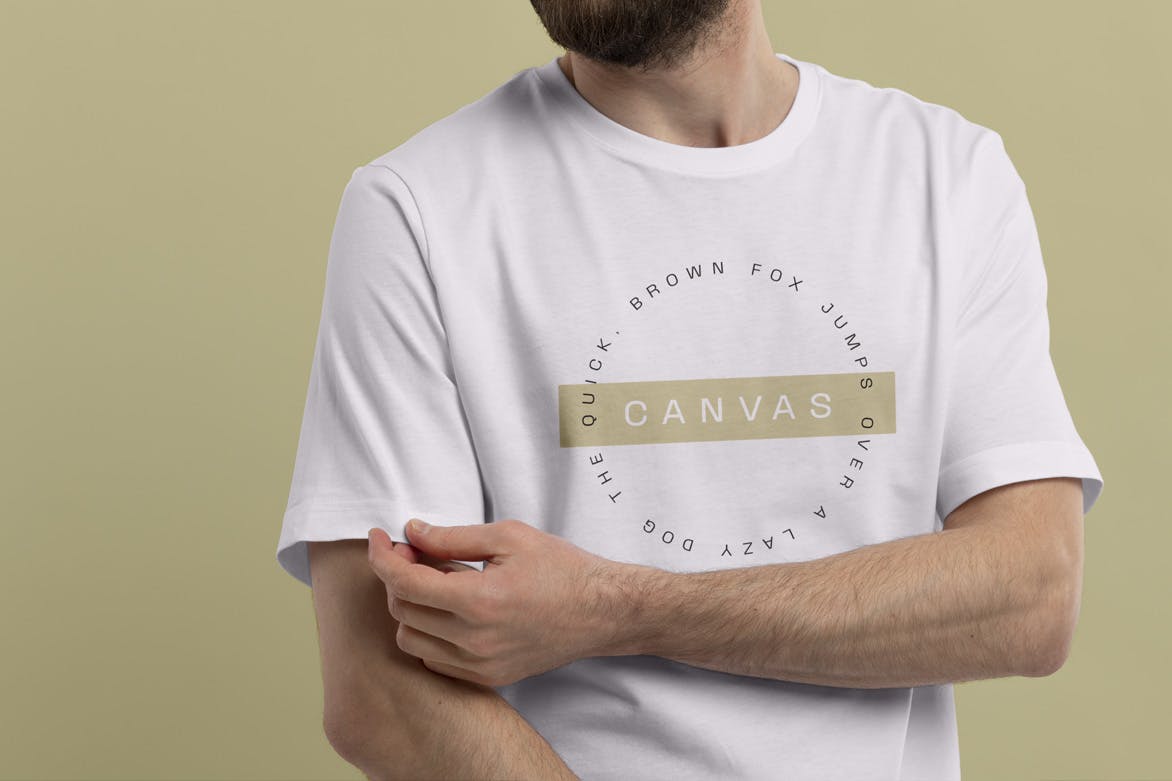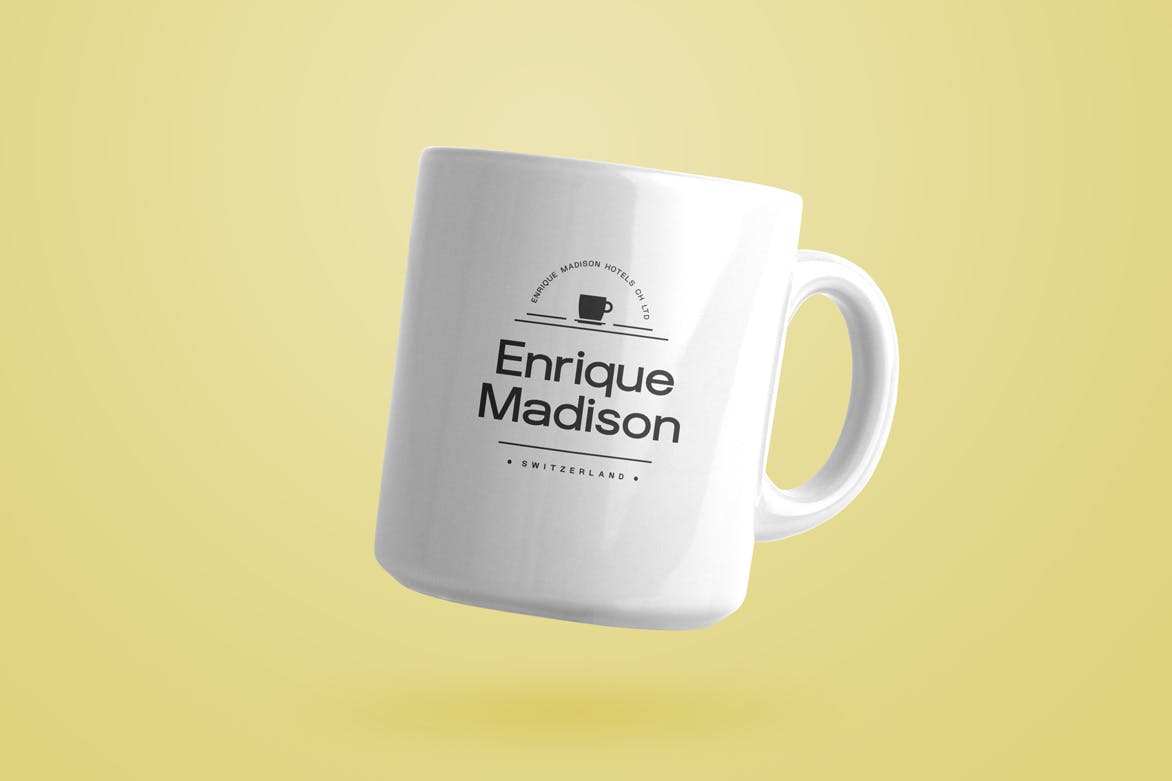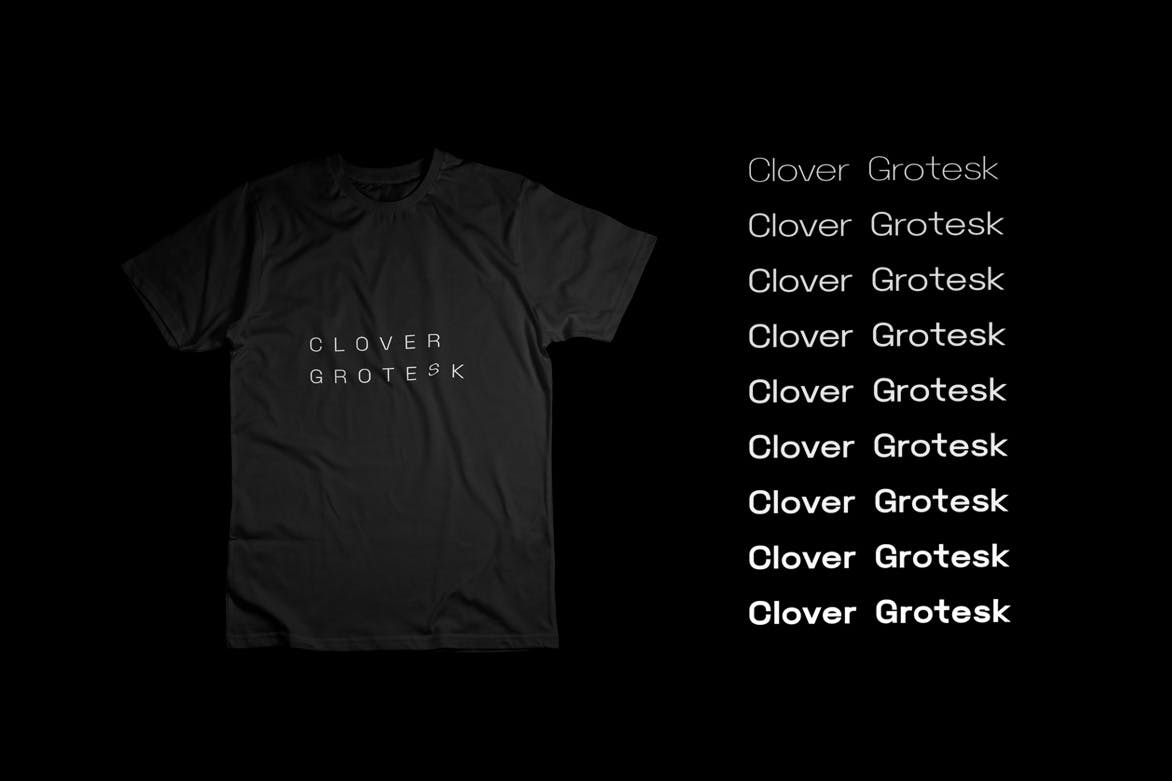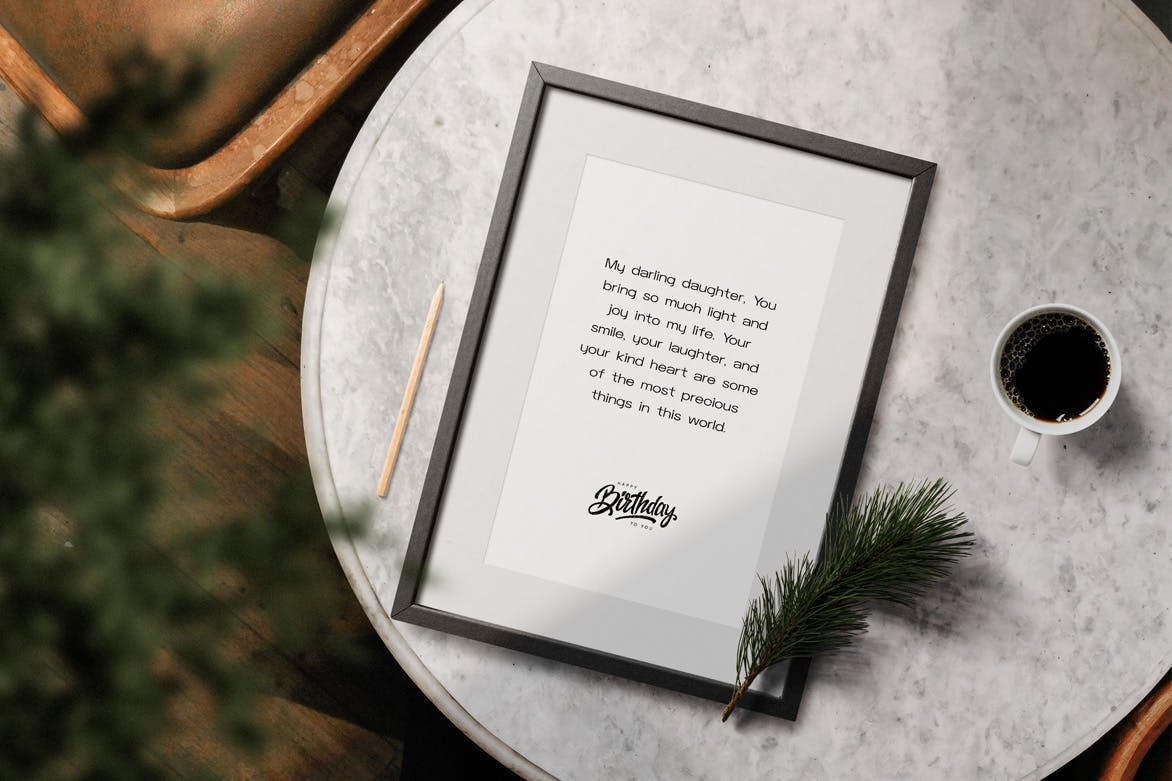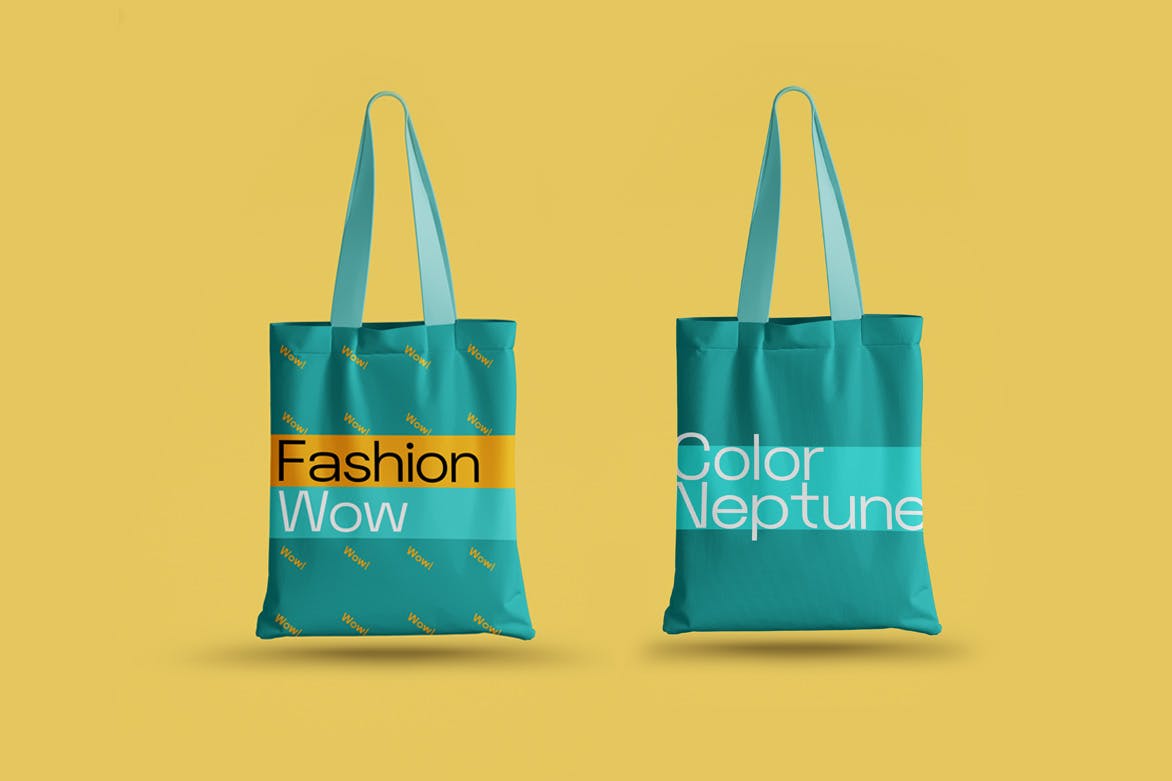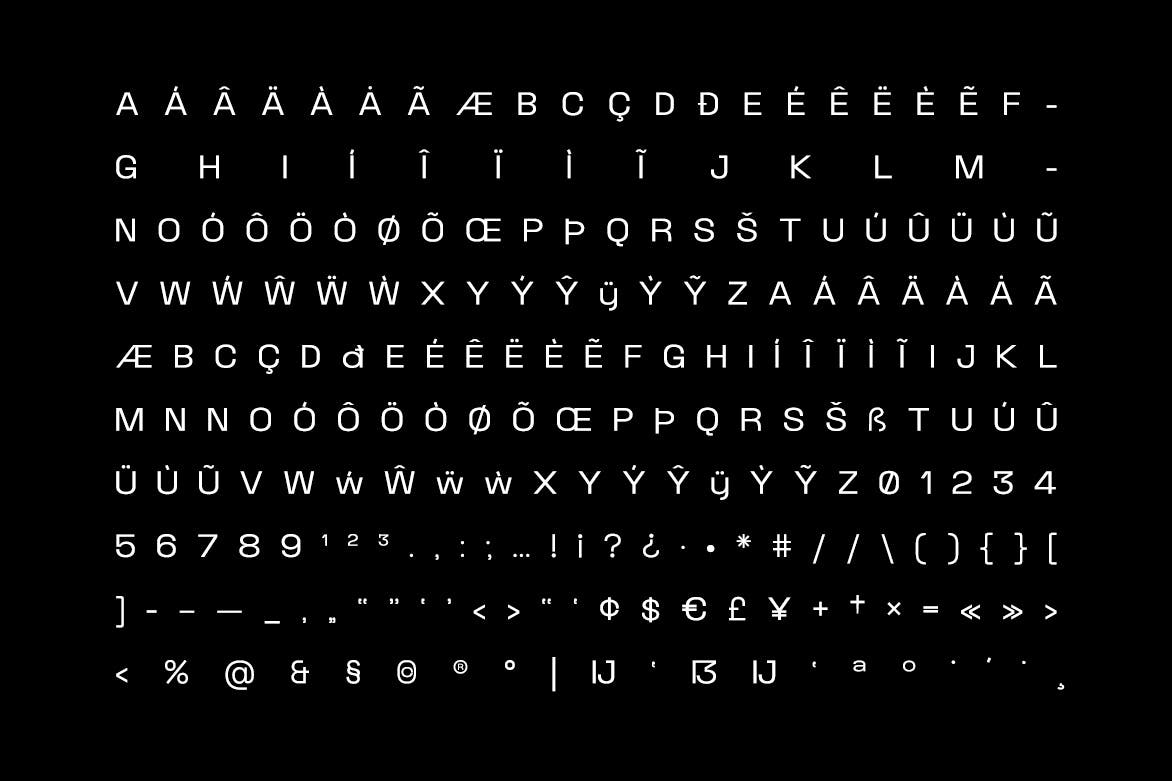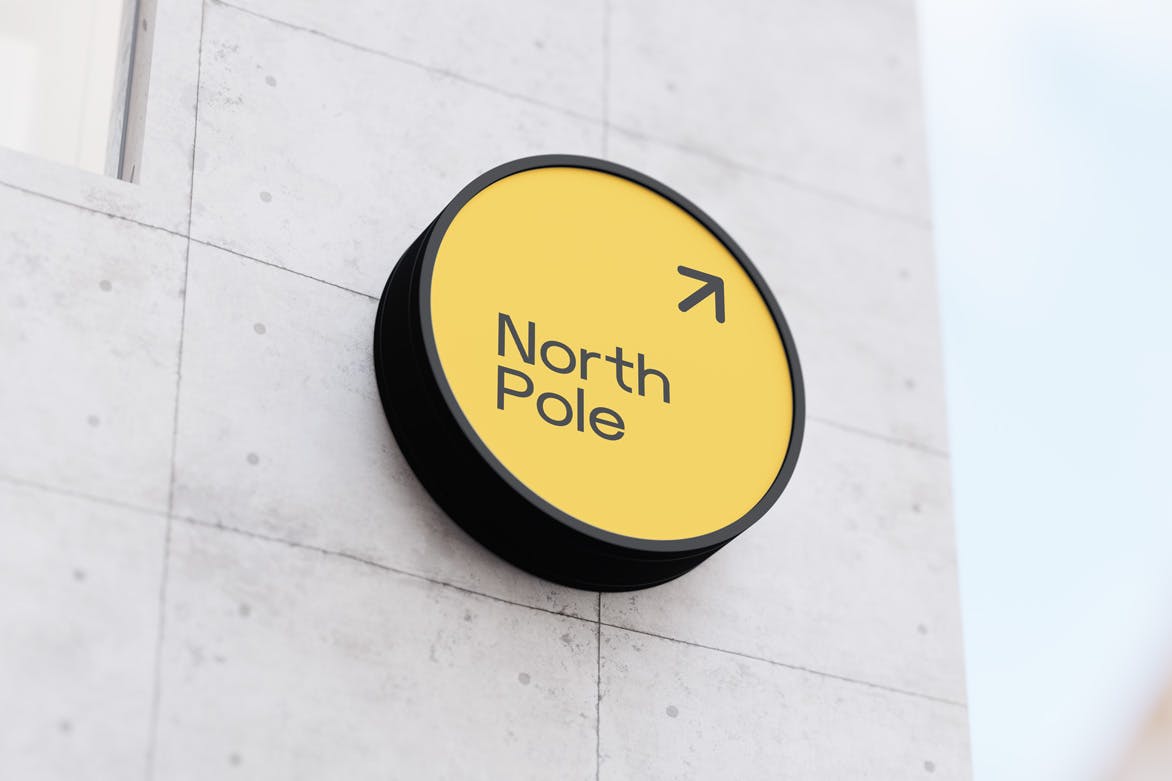
Clover Grotesk
خانواده فونت Clover Grotesk شامل ۰۹ فونت در مجموع است که شامل ۹ وزن: Thin، ExtraLight، Light، Regular، Medium، SemiBold، Bold، ExtraBold و Black میباشد. هر وزن با گلیفهای گسترده طراحی شده که مجموعهای متنوع از فونتها را به شما ارائه میدهد.
فونت Clover Grotesk بسیار انعطافپذیر و مناسب برای انواع کاربردها از جمله طراحی گرافیک، ارائه متن، طراحی وب و چاپ، و نمایش است. این فونت بهویژه برای طراحی برندینگ و لوگو، مواد تبلیغاتی، بنرها، پوسترها، تابلوها، هویتهای شرکتی و طراحیهای ویرایشی بسیار مناسب است.